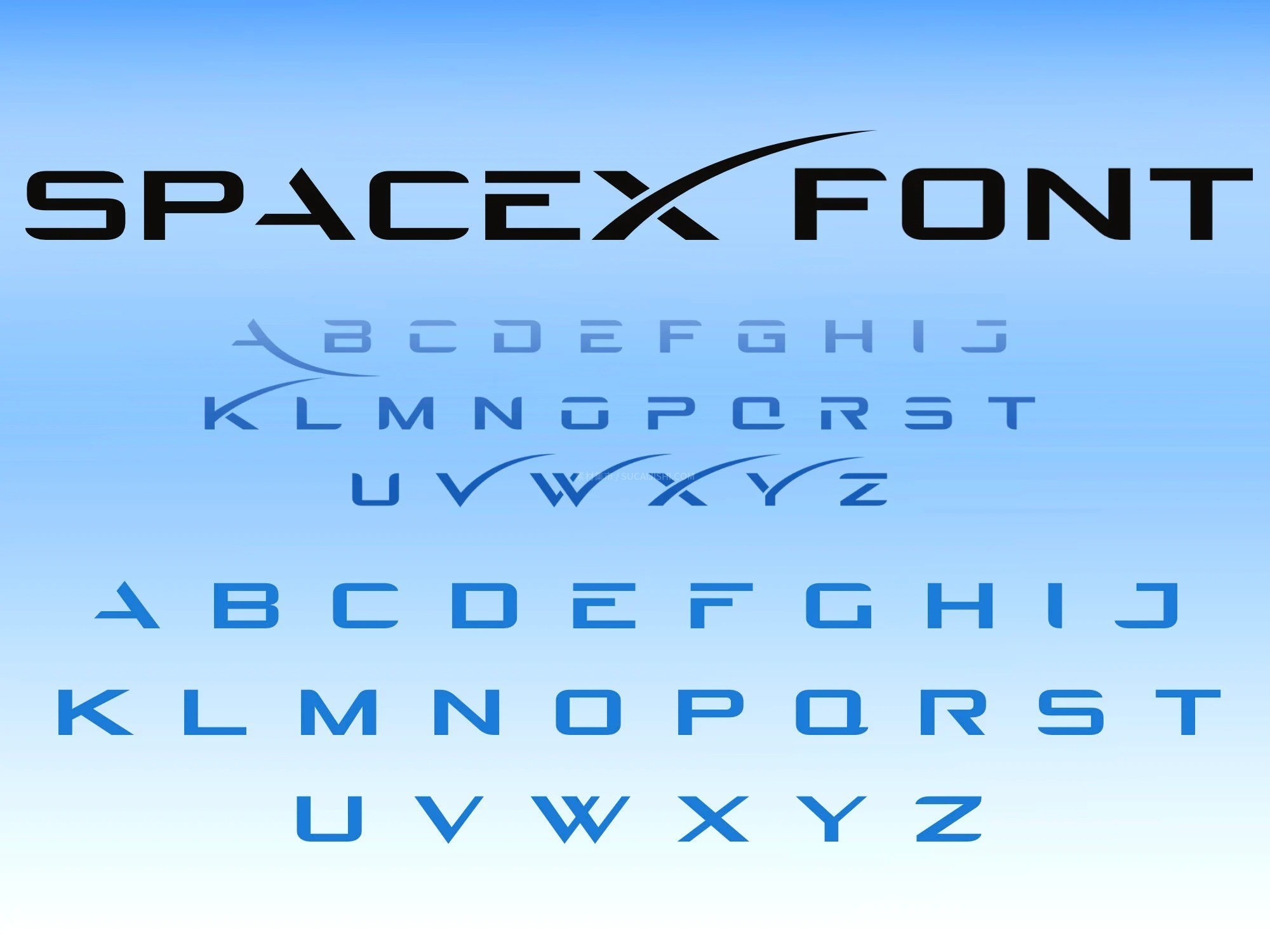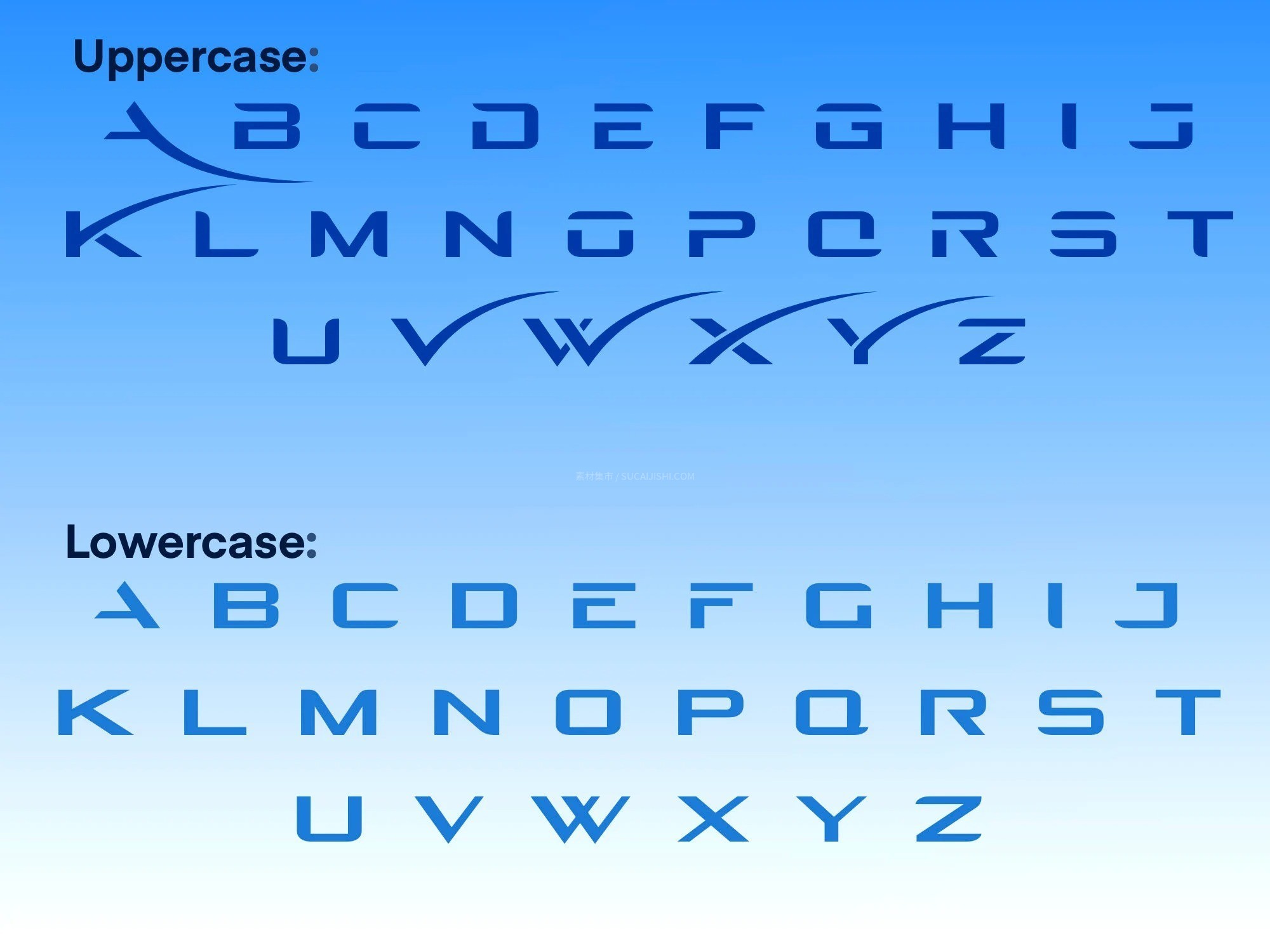
SpaceX品牌Logo字体复刻版
想要拥有马斯克同款的太空科技感?SpaceX标志性的字体绝对是未来感设计的典范!虽然官方原版字体不对外公开,但这款高度相似的无衬线替代字体(原型接近MedRida)完美还原了速度与突破性技术的魅力。特别是字母“X”那道犹如火箭飞行轨迹的艺术曲线,瞬间拉满科技氛围。带你探索顶级创意团队RO-Studio操刀的深蓝宇宙美学,为你的科技向设计注入无限可能!